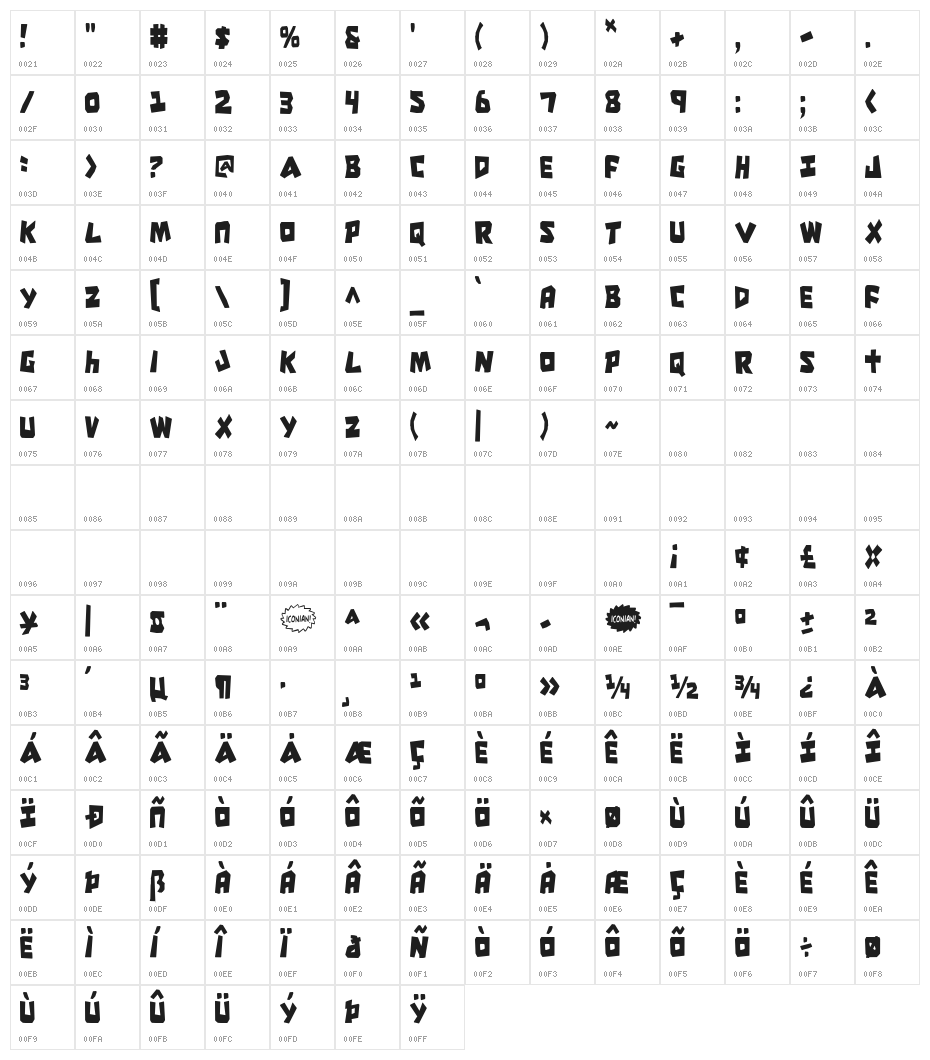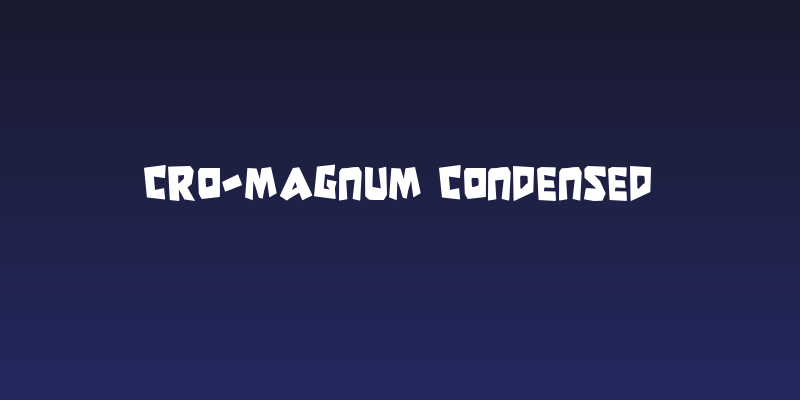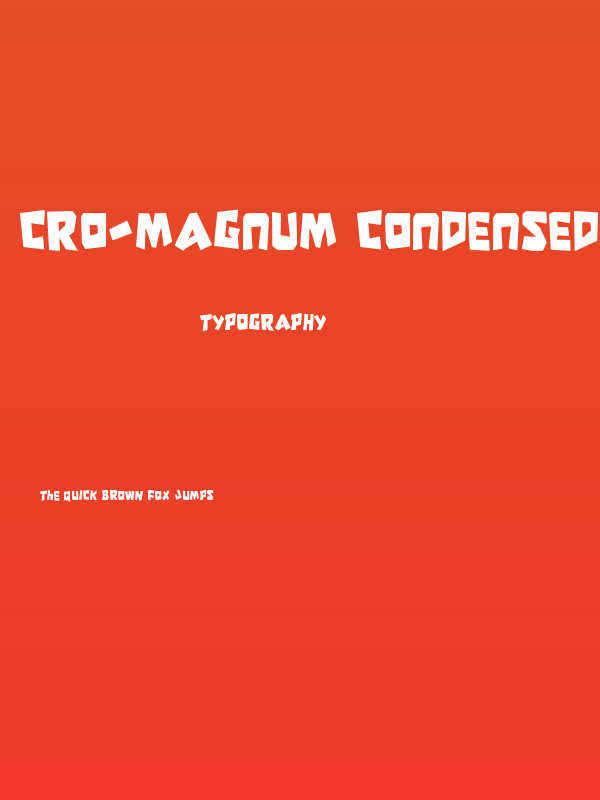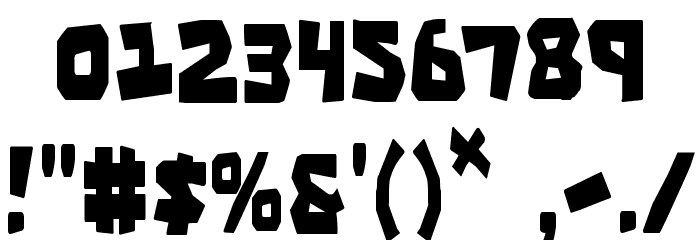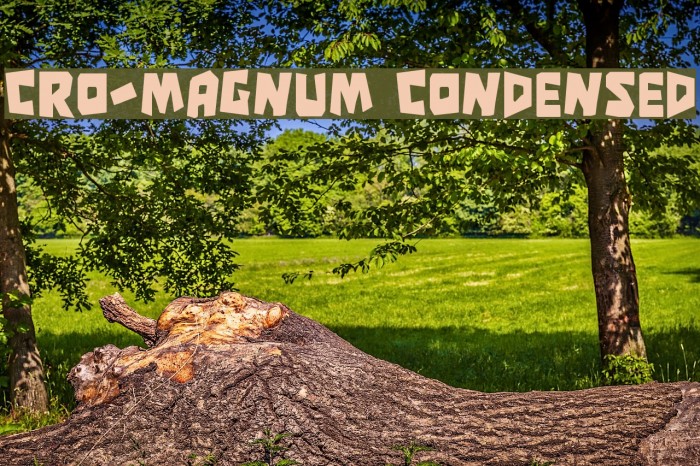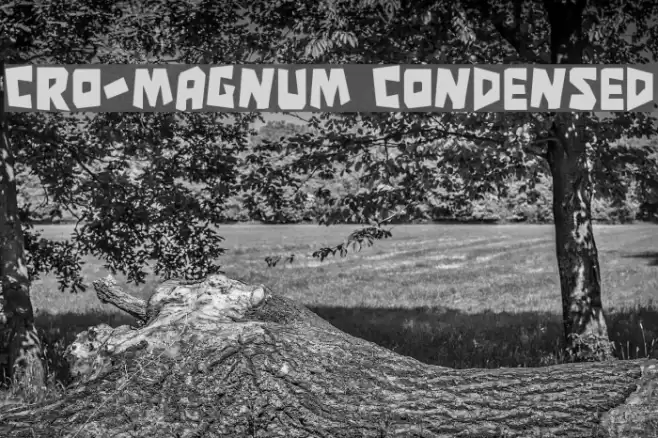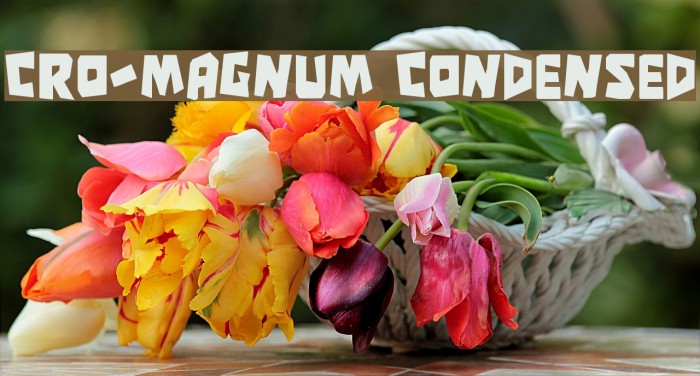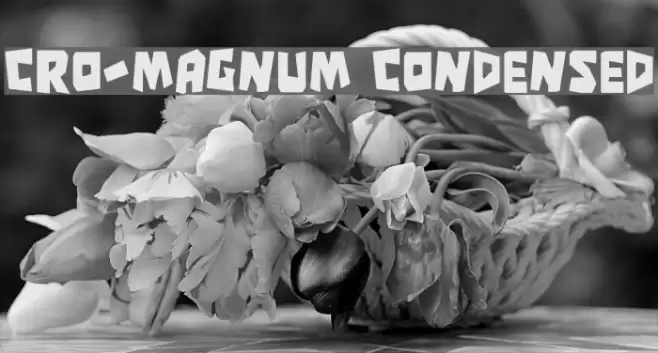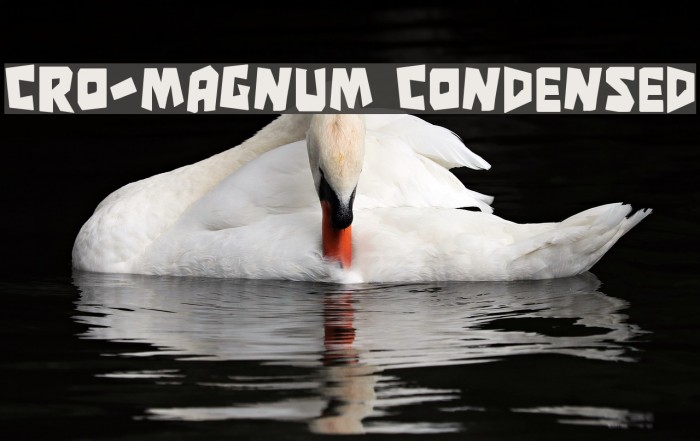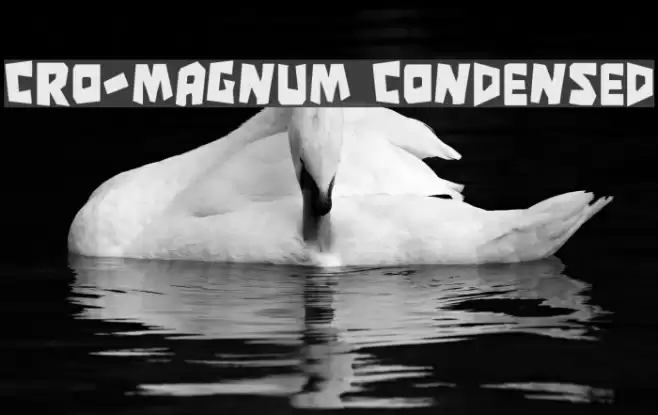
Cro-Magnum Condensed Font
| Projets proposés | Ideal for posters, logos, branding, and any project requiring a bold, attention-grabbing typeface with a unique, historical flair. |